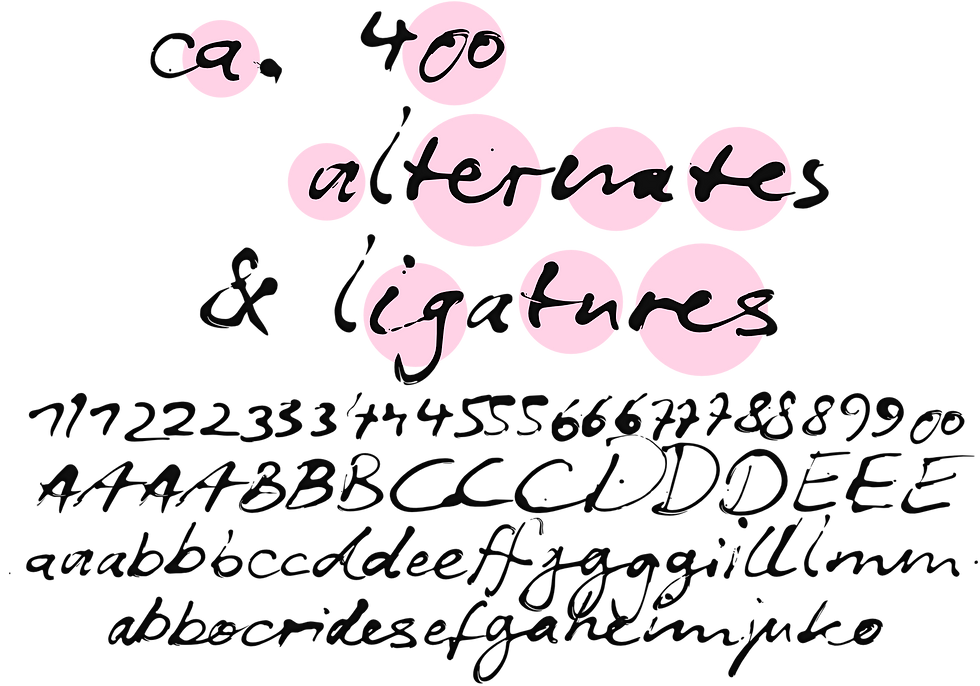
Eine Schrift aus der Tube
Die »Tube Script« ist eine individuelle Handschrift mit einem etwas nassen Charakter.
In diesem Fall war das „Schreibgerät“ eine Tube voller schwarzer Farbe. Dass sich damit nicht wirklich „schön“ schreiben lässt ist leicht nachzuvollziehen.
Trotzdem ist die Tube Script eine reizvolle persönliche Handschrift, deren ungelenken Ursprung man ihr in kleinen Schriftgrössen gar nicht ansieht.
Ist sie aber gross genug, dann zeigen sich all die Eigenheiten, die das zum Schreibgerät zweckentfremdete Farbbehältnis so mit sich bringt.
Mal ist der Strich sehr dünn und zart, ein ander Mal ist es einfach nur ein fetter Klecks, der einen Buchstaben darstellen soll, je nachdem wie stark die Tube gedrückt worden ist.
Dass dabei auch einmal ein paar Spritzer danebengehen ist nicht zu vermeiden.
Diese Zufälle des malerischen Schreibens verleiht dieser Schrift ihren Reiz. So entstehen organische Formen, zufällige Effekte, Brüche, Verschmierungen, wo normalerweise der Schreiber die Form bestimmt.
Und so passt diese Schrift hervorragend zu allem, was organisch, malerisch, handgemacht, persönlich oder auch zufällig, unvorhersehbar oder einfach nur natürlich ist.
Hunderte an Ligaturen lassen die Buchstaben der Tube Script je nach Kombination jedes Mal in einer anderen Form erscheinen.
Und über hundert alternative Zeichenformen lassen sich über die entsprechenden OpenType-Features auswählen und ermöglichen damit noch mehr Abwechslung im Schriftbild.
So ergibt sich der typisch unruhige, extrem abwechslungsreiche Eindruck einer wirklich individuellen Handschrift – fast wie wirklich handgeschrieben.